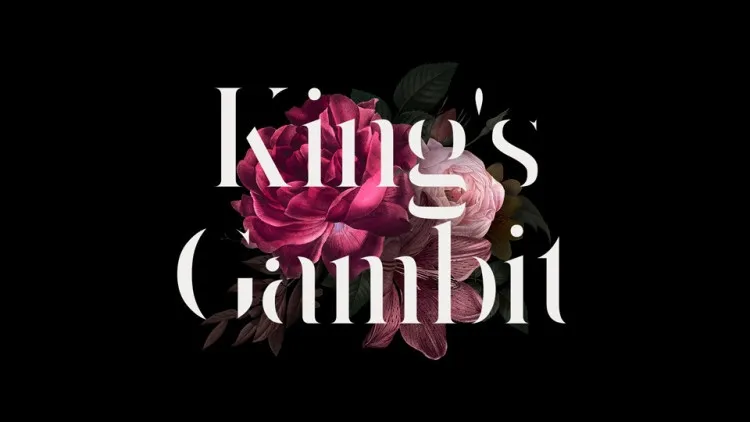
Olá! A fonte King’s Gambit Serif é uma tipografia moderna e fashionista. Inspirada nas marcas de alta moda que dominam o cenário atual, essa elegante tipografia possui traços grossos e acentuados, oferecendo um toque de personalidade. Ela se destaca perfeitamente tanto para cabeçalhos quanto para texto de corpo, especialmente em pesos mais pesados. Seu design simples mas avançado transmite uma sensação elevada e sofisticação a qualquer produto que ela atinge. Estamos honrados em compartilhá-la com o designer Matthew Welch.